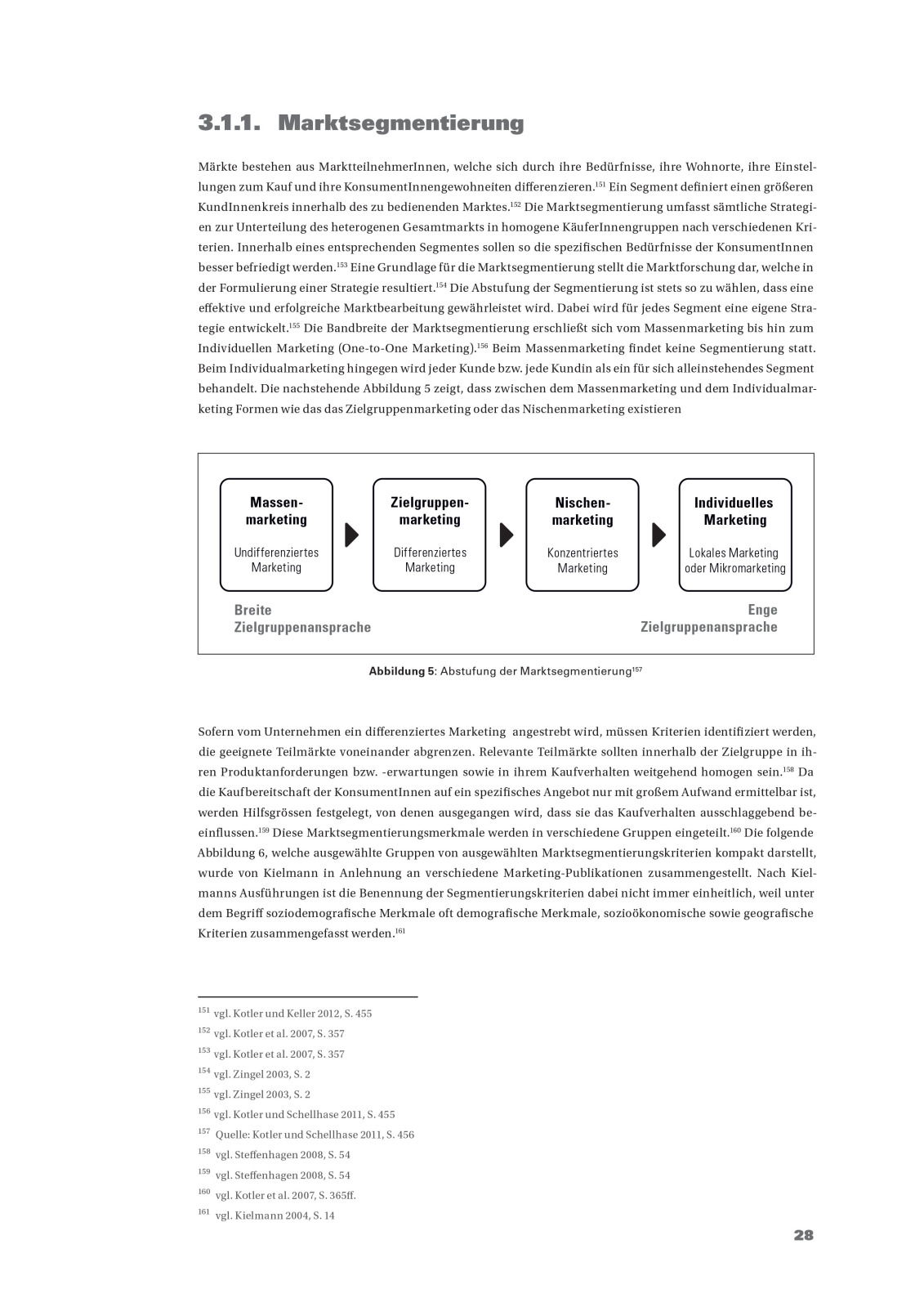
Calibri (Textkörper) - Welchen Überschriften-Font?
Hallo ich bräuchte einen Ratschlag:
Ich habe meinen Fließtext mit der Calibri Schrift formattiert. Jetzt bin ich auf der Suche nach einem
Überschriften-Font die Cambria Schriftart gefällt mir aber gar nicht.
Welche alternative würde sich hier anbieten?
die vorgeschlagene Schriftart muss keinesfalls und zwangsläufig eine Windowssystem Schrift sein.
Wieviel Budget steht denn zur Verfügung? Mit welchen Programmen/Betriebssystem arbeitest Du? Und um welche Art Publikation handelt es sich denn? Wie würdest Du das inhaltliche Thema umschreiben? Sind perspektivisch Webanwendungen geplant?
Edit: Oh … ich lese gerade Du bist Student. Ich nehme an »nur« für eine Hausarbeit oder Ähnliches?
Korrekt eigentlich »nur« für eine Abschlussarbeit.
aber über die Standard Combi bin ich nicht zu frieden.
wie gesagt schlag was - auf der uni haben wir sicher die eine bzw. andere schirftart lizensiert.
Als optischer Anhaltspunkt:
den anhaltspunkt verstehe ich nicht
wie gesagt schlag was
auf der uni haben wir sicher die eine bzw. andere schirftart lizensiert
??? :shock: Ist ja auch mal eine konstruktive Antwort. Überhaupt kein Schwamm drin …
nun ja wie gesagt, das ist nun mal die Tatsache, was ich damit nur sagen wollte ist, dass mal vom Budget abgesehen werden soll, denn vielleicht haben wird die ja auch dort. Das soll keine Einschränkung sein.
Na da schau’n wir mal.
Ich persönlich würde eine Serife mit humanistischem »Einschlag« und »weicher« Anmutung wählen, beispielsweise:
· Milo Serif (idealerweise besser mit der Milo statt der Calibri kombiniert)
· Corda
· Sina Nova
· Pona
· Dolly
Aber auch »experimentellere« Ansätze könnten funktionieren:
· Le Monde Courier (falls vorhanden lieber die Le Monde Sans dazu)
d.h. statt der Calibri die Milo Serif im Textkörper?
und als Headline die vorgeschlagene?
Bei der Le Monde Combi
sans als Fließtext oder Headline?
ach ja mit Vorzug eine Schrift aus der Linotype-Serie:
inhaltich es geht um , Diversity-Management, Diversity, Diversity-Marketing
Deine scheibchenweise Informationspolitik nach dem Motto »bedient mich und wenn Ihr noch etwas braucht, zieht es mir aus der Nase« finde ich ja nicht gerade zielführend. Wie wäre es, wenn Du uns mal etwas mehr entgegen kommst? Stell Dir vor, Du redest mit Leuten, die weder vom Thema noch von der Ausstattung Deiner Uni eine Ahnung haben und plaudere einfach mal etwas aus dem Nähkästchen … sonst wird es ein Fischen im Trüben bleiben und alle sind am Ende nur frustriert.
Diversität worin (btw (sic!) wo ist denn das schöne theutsche Wort abgeblieben)? Biologie? Ökologie? Pleitepapiere von Banken? Meinungen?
Tu mal ein büschen Budda bei die Fische tun!
Hat noch keiner Minion/Myriad gesagt? :hammer:
Gut auf jeden Fall hast du Recht - mit dem Motto so die friss oder stirb komme ich auf jeden Fall nicht zu einem konstruktiven Ergebnis.
Das ist meine Ausgangslage.
Im Moment arbeite ich mit Word 2010 und verwende die Standardtypo Kombi
Für die Überschriften: Cambria (Überschriften)
Für den Fließtext: Calibri (Textkörper)
Bei dem Text dem ich eine Facelifting verpassen möchte geht es um wirtschaftliche/ökonomische Themen.
ich habe mich schlussendlich für die Univers und Utopia Kombi entschieden.
Die Fußnotenziffern werden nur im Text kleiner gemacht und hochgestellt. Aber vor der Fußnote gibt es keinen Grund, so zu verfahren, auch wenn Word es so macht. Im Text sollte die Ziffer nicht groß auffallen, aber vor der Fußnote sucht man sie, also sollte sie in der normalen Schriftgröße der Fußnoten gesetzt sein und schon gar nicht hochgestellt, das macht es unnötig unruhig.